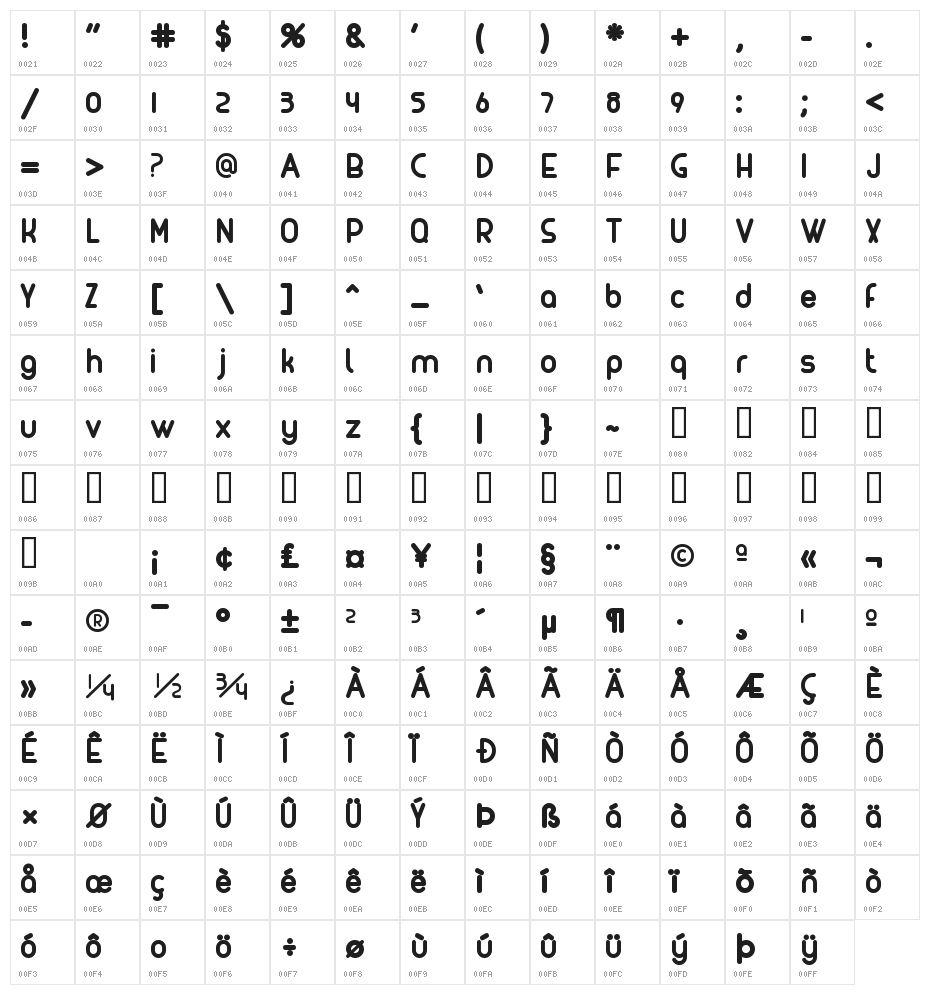
MAXWELL BOLD Font
| 使用场景 | Headlines, Logos, Branding |
| 推荐项目 | Ideal for branding, signage, headlines, and digital content where a modern and approachable look is desired. |